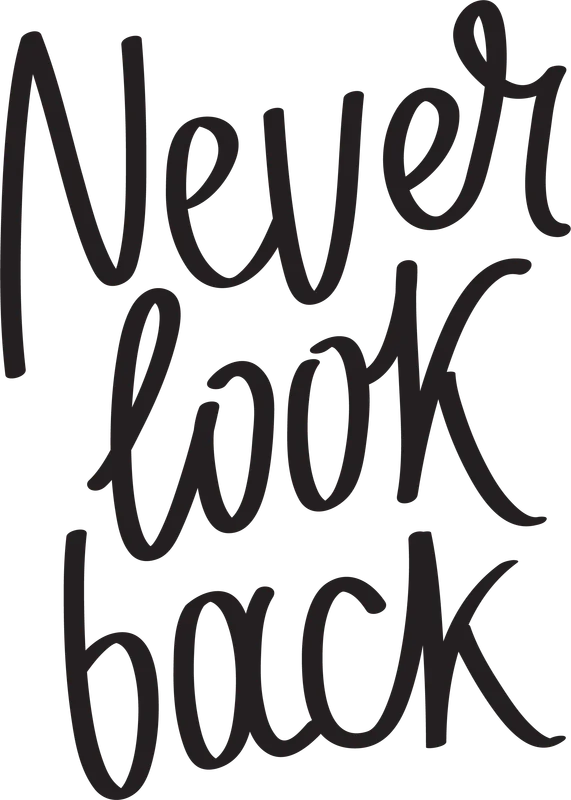
Thông điệp "Never look back" ý nghĩa, font chữ thư pháp
Thông điệp "Never look back" ý nghĩa, font chữ thư pháp — In hình ảnh "Never look back" với font chữ thư pháp độc đáo, truyền cảm hứng cho mọi sản phẩm. Phù hợp in chuyển nhiệt, DTF.
Trong hình có: chữ viết, thông điệp
Phong cách: line-art · Cảm giác: mạnh mẽ
Tông màu chủ đạo: đen